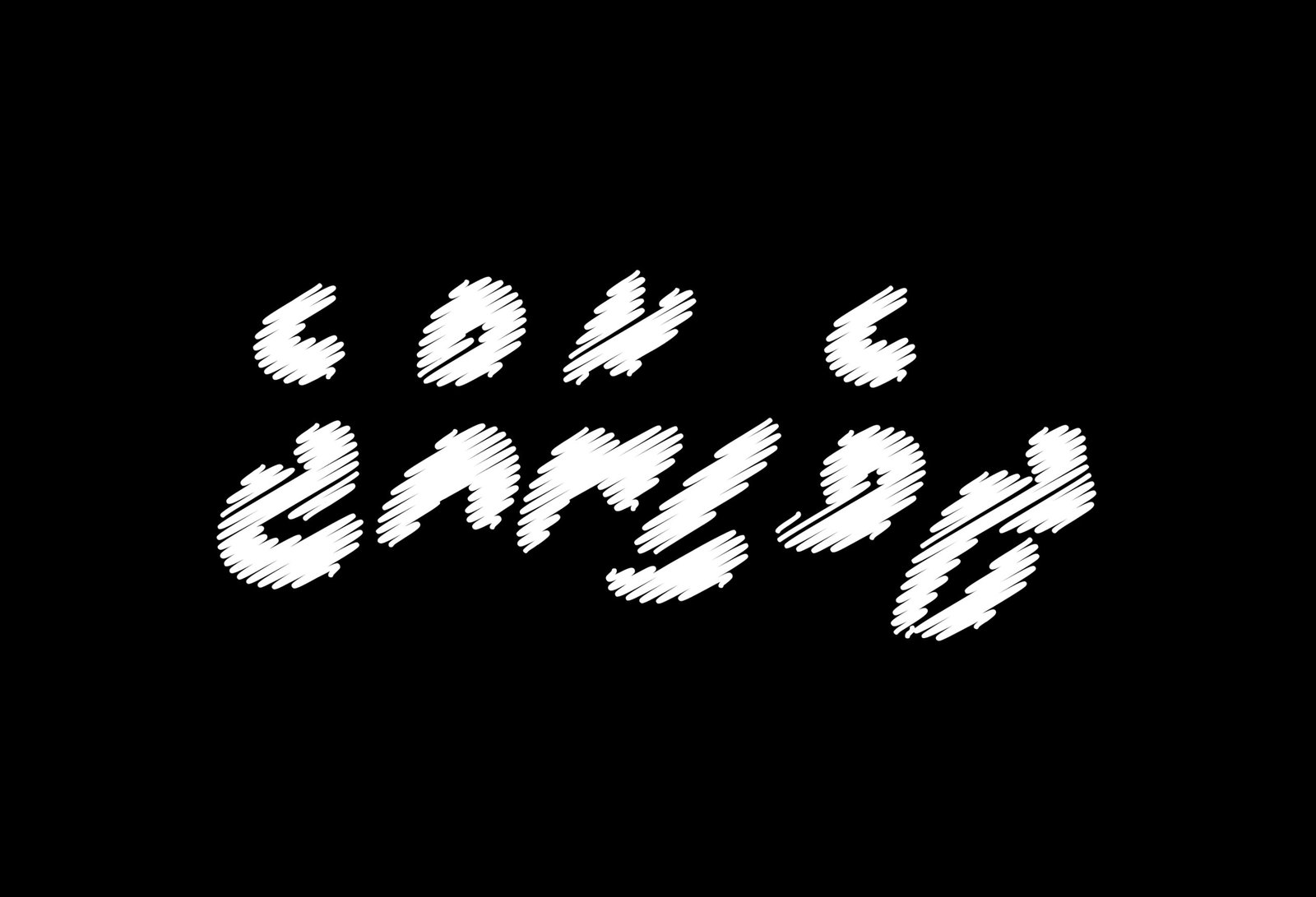
އެމް.ވީ އިޒްޔަން ސްކްރިބްލް
އެމް.ވީ އިޒްޔަން ސްކްރިބްލް (MV Izyan Scribble)** އަކީ ސުރުޚީތަކަށް ޚާއްޞަކޮށްގެން ފަރުމާކޮށްފައިވާ ފޮންޓެކެވެ. މިއީ ގަލަމުން ރޮނގުތައް އަޅައިގެން ފުރިހަމަ ކޮށްފައިވާ އަކުރުތަކެއް ގޮތަށް ފަރުމާކޮށްފައިވާ ފޮންޓެކެވެ. މި ފޮންޓު އެންމެ ބޮޑަށް ޚާއްޞަކޮށްފައިވަނީ ބޮޑެތި އިޝްތިހާރުތަކަށާއި، ފޮތުގެ ބޭރުގަނޑަށާއި، މަޖައްލާތަކުގެ ސުރުޚީތަކުގެ އިތުރުން ޑިޖިޓަލް މީޑިއާގެ ސުރުޚީތަކަށެވެ.
### ސްކްރިބްލް ސްޓައިލަށް ތާނަ ފަރުމާކުރުން
ތާނަ އަކުރުތަކަކަށް “ސްކްރިބްލް” ނުވަތަ އަތުން ކުރަހާފައިވާ ފަދަ ސްޓައިލެއް ގެނައުމަކީ ތަފާތު ގޮންޖެހުންތަކަކާ ކުރިމަތިލާންޖެހޭ ކަމެކެވެ. އަދި ކިޔަން ފަސޭހަވާނެގޮތަކަށް ފަރުމާ ކުރަން މަސައްކަތް ކުރެވުނެވެ.
އެމް.ވީ އިޒްޔާން ސްކްރިބްލް ފަރުމާކުރުމުގައި ބޭނުންކޮށްފައިވާ މުހިންމު ފަންނީ އަދި ޑިޒައިންގެ ތަފުސީލުތައް ތިރީގައި އެވަނީއެވެ:
އެމް.ވީ އިޒްޔަން ސްކްރިބްލްގެ ޚާއްޞަ ސްޓައިލްގެ ސަބަބުން ކުދިކޮށް ދިގު ލިޔުންތައް ލިޔެފައި ހުންނައިރު އުނދަގޫ ވެދާނެއެވެ.
އެންމެ ރަނގަޅަށް ބޭނުންކުރެވޭނެ ގޮތްތައް
* **ފޮތުގެ ބޭރުގަނޑާއި މަޖައްލާގެ ސުރުޚީތައް:** ވާހަކަ ފޮތްތަކަށާއި، ޅެން ފޮތްތަކަށް
* **ޑިޖިޓަލް މީޑިއާގެ ސުރުޚީތައް:** ވީޑިއޯ ތަމްބްނެއިލްތަކަށާއި، ޑޮކިއުމެންޓްރީތަކުގެ ނަން އަދި ސޯޝަލް މީޑިއާގެ ޕޯސްޓުތަކުގައި ބޭނުންކުރުމަށް ވަރަށް އެކަށީގެންވެއެވެ. އާންމު ފޮންޓުތަކަށްވުރެ މިއީ މާ ޝައުޤުވެރި ގޮތެކެވެ.